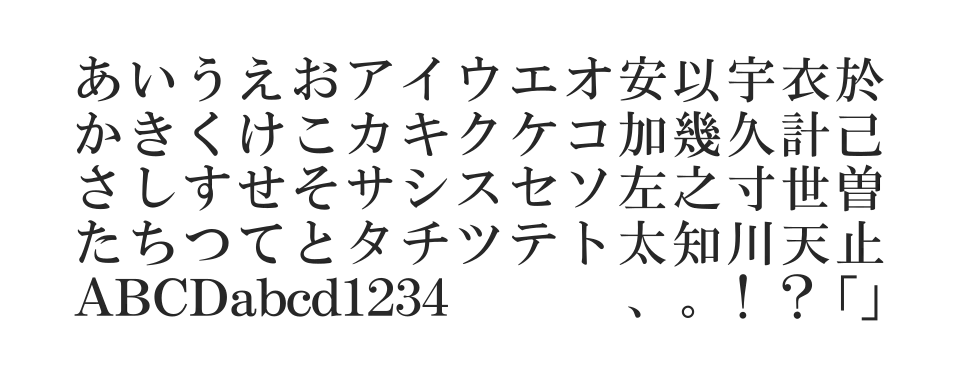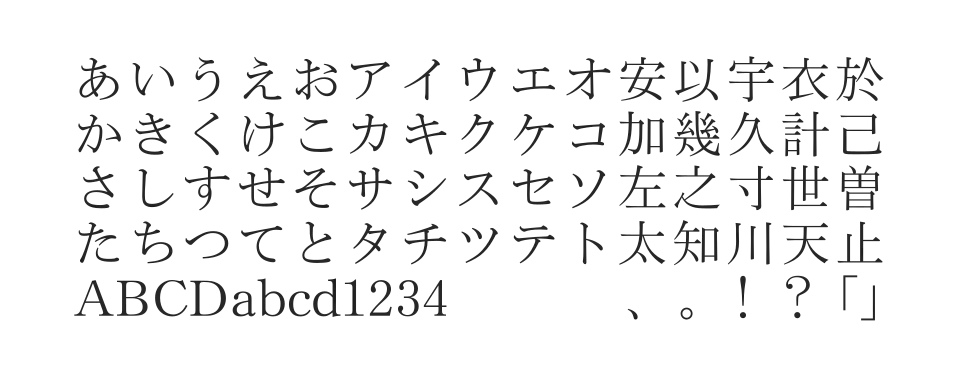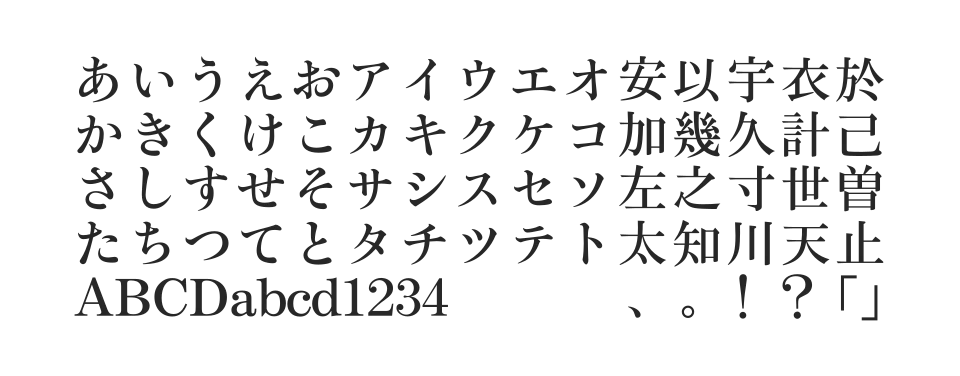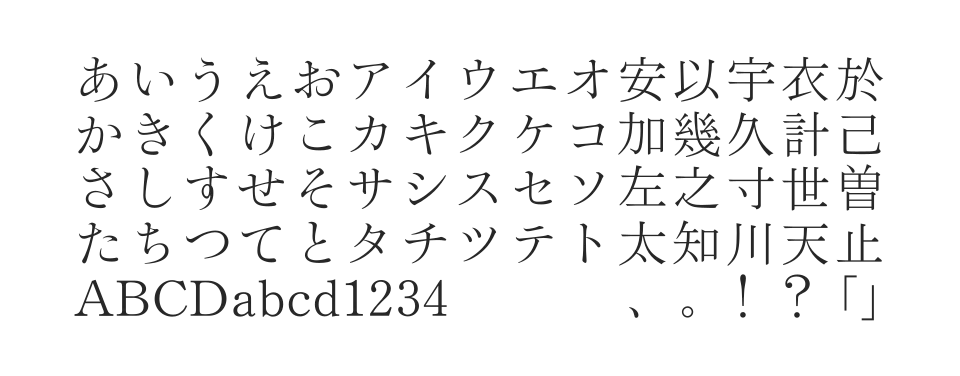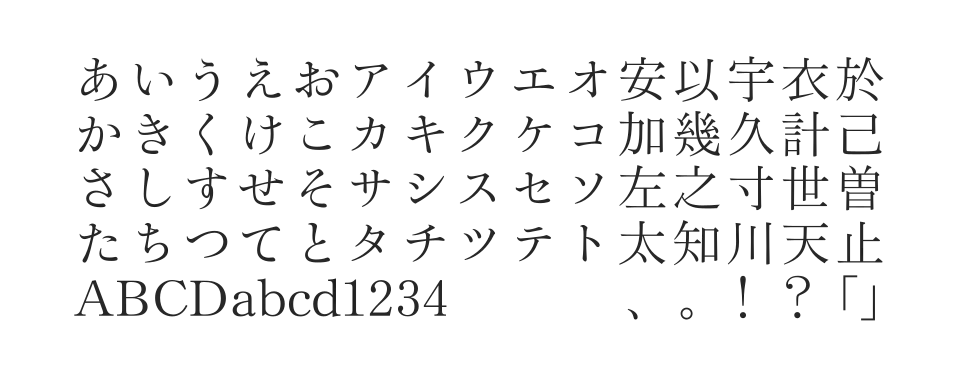
しなやかなカーブとキレのある直線を調和させた、可読性の高い本格派の本文用明朝体。新小がなバリエーションでPr5仕様の20,317文字を収録。
しなやかなカーブとキレのある直線を調和させた、可読性の高い本格派の本文用明朝体。新小がなバリエーションでPr5N仕様の20,317文字を収録。
しなやかなカーブとキレのある直線を調和させた、可読性の高い本格派の本文用明朝体。新がなバリエーションでPr5仕様の20,317文字を収録。
しなやかなカーブとキレのある直線を調和させた、可読性の高い本格派の本文用明朝体。新がなバリエーションでPr5N仕様の20,317文字を収録。
本明朝新がなのPro版で、Adobe-Japan1-4準拠により15,444文字を収録。新がなの魅力を活かしつつ、より多くの文字に対応した書体です。
本明朝の新がなバリエーション。勢いのある筆の運びが印象的なデザインで、従来の明朝体とは異なる表情を持つ書体です。
本明朝のPr5版で、Adobe-Japan1-5準拠により20,317文字を収録。高品質な組版に対応し、プロフェッショナルな印刷物に最適です。
本明朝の最新版で、Adobe-Japan1-5準拠により20,317文字を収録。JIS2004字形に対応し、現代的な組版ニーズに応える明朝体です。
本明朝のPro版で、より多くの文字セットに対応。Adobe-Japan1-4準拠で15,444文字を収録し、DTPや書籍制作に最適な明朝体です。
しなやかなカーブとキレのある直線を調和させた、可読性の高い明朝体。本文組みから見出しまで幅広く使用でき、和文書体を代表する本格派の本文用明朝体です。